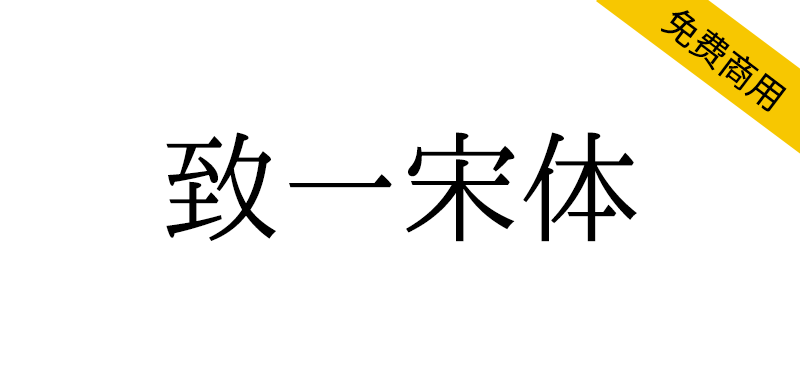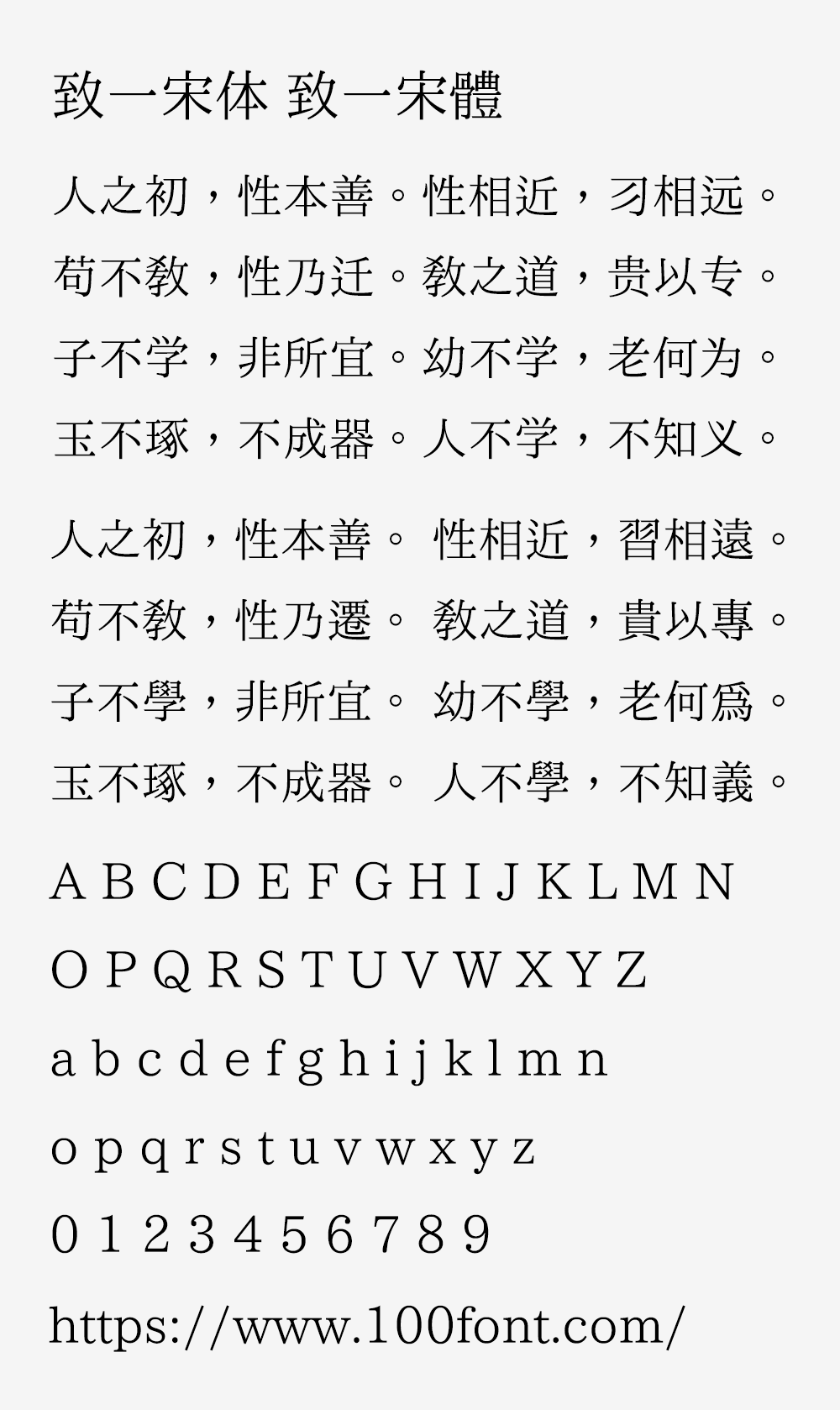
虽世殊事异,所以兴怀,其致一也。——《兰亭集序》,致一宋体(致一明朝/ 치일명조)是一套以TrueType格式封装、依照Unicode编码的OpenType字体,采用「怀有传承字形向往的折中字形」,即以传承和惯用字形为主体、多就少改,兼以传承字形笔法为基础,参考历史异形、类推隶定规则,仿写新字形,力使字理直观、优化、可分(注:优先取用传世字理和强势初理),字形通行、美观、可认、兼顾写印。
信念:「致一宋体」的信念是:基于现代隶定规律,综合选取初理与重构理据,尽己所能,力求字理直观清晰、字形美观好写。
「致一宋体」本为作者自创世界观的架空字体。最初的理念仅仅是区别字源、统一部件。最初的字形虽合古意,但是「似篆非隶,若存若亡」,体系复杂,辨识度差,自己读写都慢,就更不要指望那个世界观的角色们会用了。深入研究发现,纵观汉字发展史,字理本不可知、还要后人考证者有之,初理本不可知、千年来已有重构新字理、弃去实在可惜者有之,本系同音、近音甚至同义假借(如「开」,本读作{启},训读为{闿}),「鸠占雀巢」甚至「鸠占鸠巢」者有之,即便身世清楚,直接把字源堆到一起的「古字」大众根本不识(如「⿱爪象」,今作「为」)者亦有之。
究其原因,文字学界认为,文字是记录语言的工具,先有语言再有文字,先有文字再有正字法。文字的最根本特点是实用性,这就决定了字理的最根本特点是时代性。今人所书虽去古渐远,然笔画增损之间,实有潜藏理路可循。这就是千年书写实践所凝结的「现代隶定规律」和理据重构。「现代隶定规律」不是一对一的,而是一对多、多对一的。例如「出」「大」,作部件时多简写为「士」「土」——字理上的「出」「大」不一定写成「出」「大」,字形上的「士」「土」也未必就是「士」「土」。重构理据更是汉字传承的生命力所在。例如「幸」字,本从犬、从倒矢,理据不明,今则从夭从戟(逆),理据昭然。
传承印刷字形是「现代隶定规律」和理据重构的典范。正式版充分肯定「现代隶定规律」和重构理据,以传承字形为基础,多就少改,让字源和重构理据公平竞赛,在个人能力范围内力求在约定俗成的前提下使字理直观清晰、字形美观好写,不独是为了自创世界观的角色,亦是为了做一份文字学答卷,请天下有缘之士批评指正。